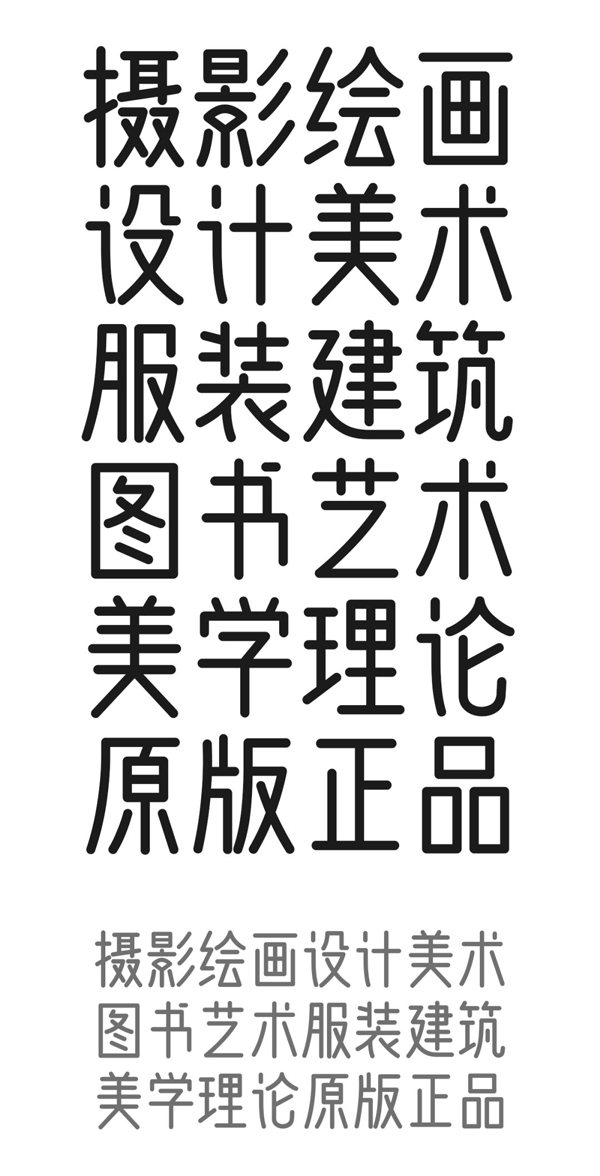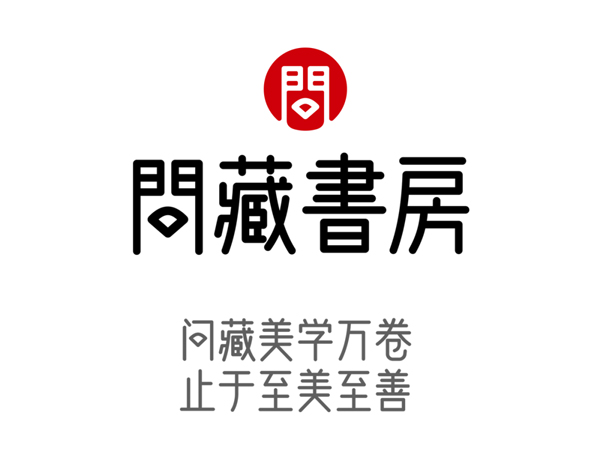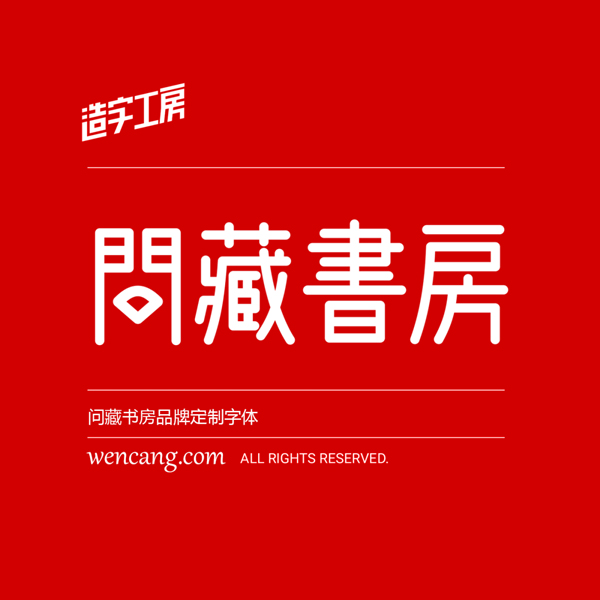
造字工房新出了一款免费可商用字体-问藏书房体
亲爱的小伙伴们,又一款免费可商用的字体上线了,由造字工房联合问藏书房倾心打造,精心制作了这款问藏书书房品牌字体。
字型特点
问藏书房字体的设计整体现代简约,中宫紧凑,视觉阅读极具层次感,字字俊秀且呈现古雅之风,设计团队以精心的设计赋予了汉字全新美感!字符编码采用中华人民共和国GB2312-80字符集标准,按需添加101个汉字。共收容字数6864CJK汉字,ASCII常用字符100个。
这款字体既拥有女性柔美的风格,又具有古雅的气质,喜欢的小伙伴都去下载了,感谢造字工房字库设计人员的辛苦劳作和无私奉献,葱花粉你了。